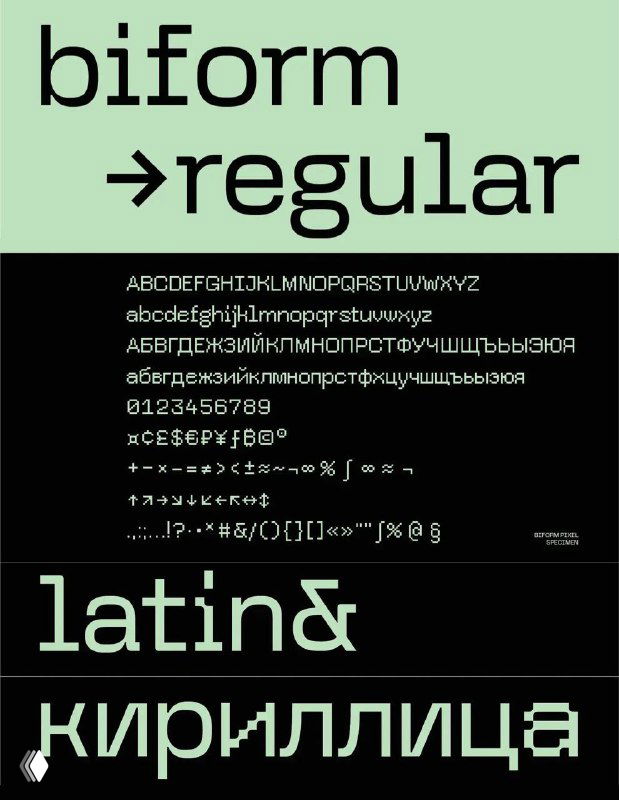
Технологичный моноширинный гротеск с базовой и декоративной версией, которые можно смело сочетать. Хорошо подойдёт для оформления заголовков, постеров, обложек и других задач. Цена — от 2 250 ₽ за начертание.